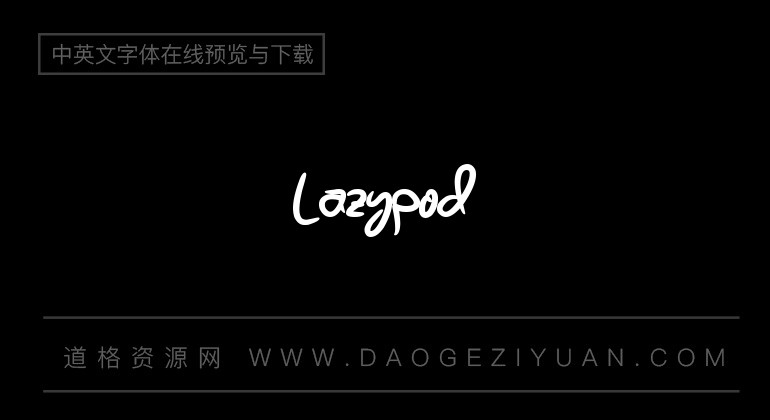
Lazypod 字体是一款拥有极具视觉冲击力的屏幕字体,它采用简约设计风格,拥有流畅的线条,清晰的轮廓,以及大胆的曲线。它的字体特征让它可以在任何屏幕上都能够显示出突出的效果,同时也能够让文字的内容更加清晰明了。Lazypod 字体也可以用于多种不同的媒体,包括网站、印刷品、电子邮件、手机应用等,是一款非常适用的字体。内容介绍
Lazypod是一款非常不错的手写艺术字体,具有很好的视觉感,适合于文化类的宣传设计、商业类品牌的广告和产品包装设计以及个性化文字排版等较多场景。